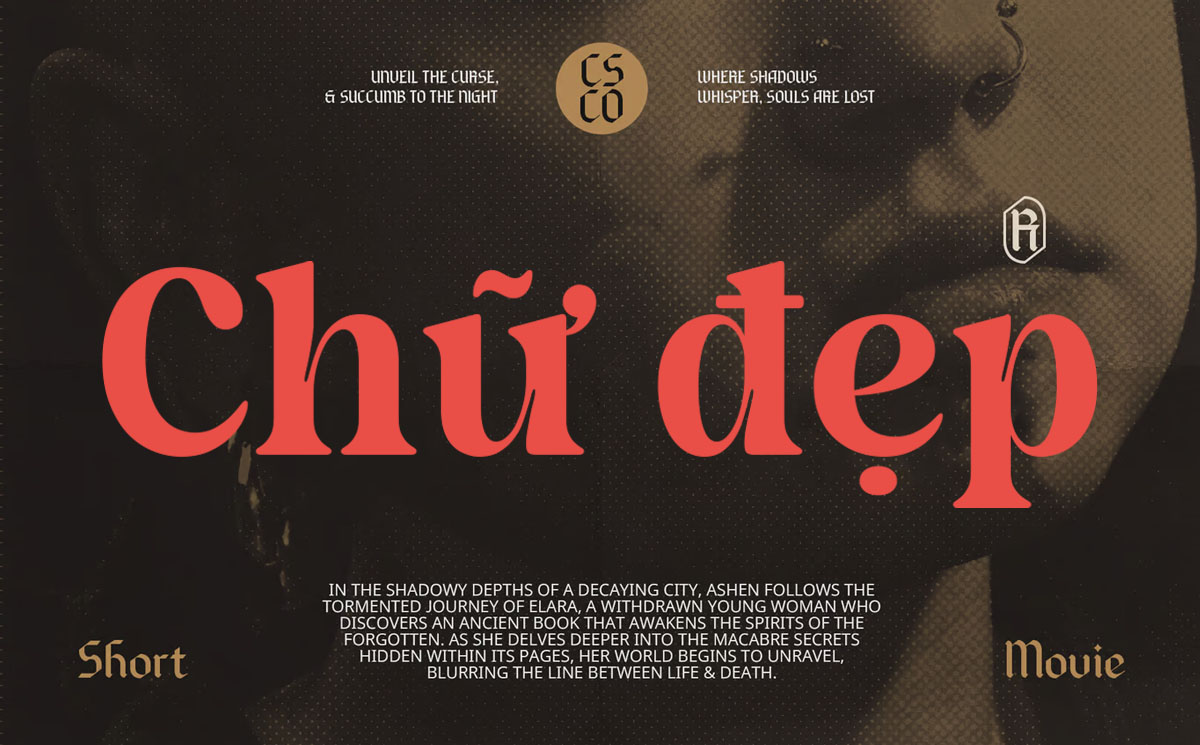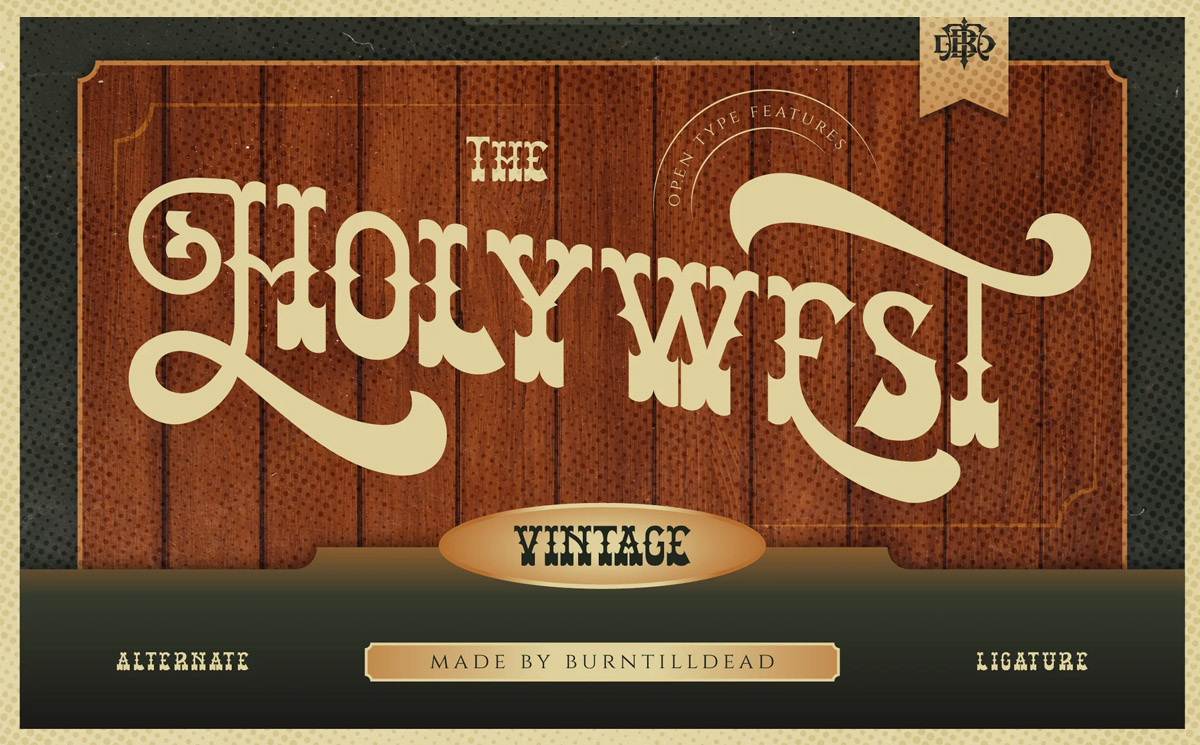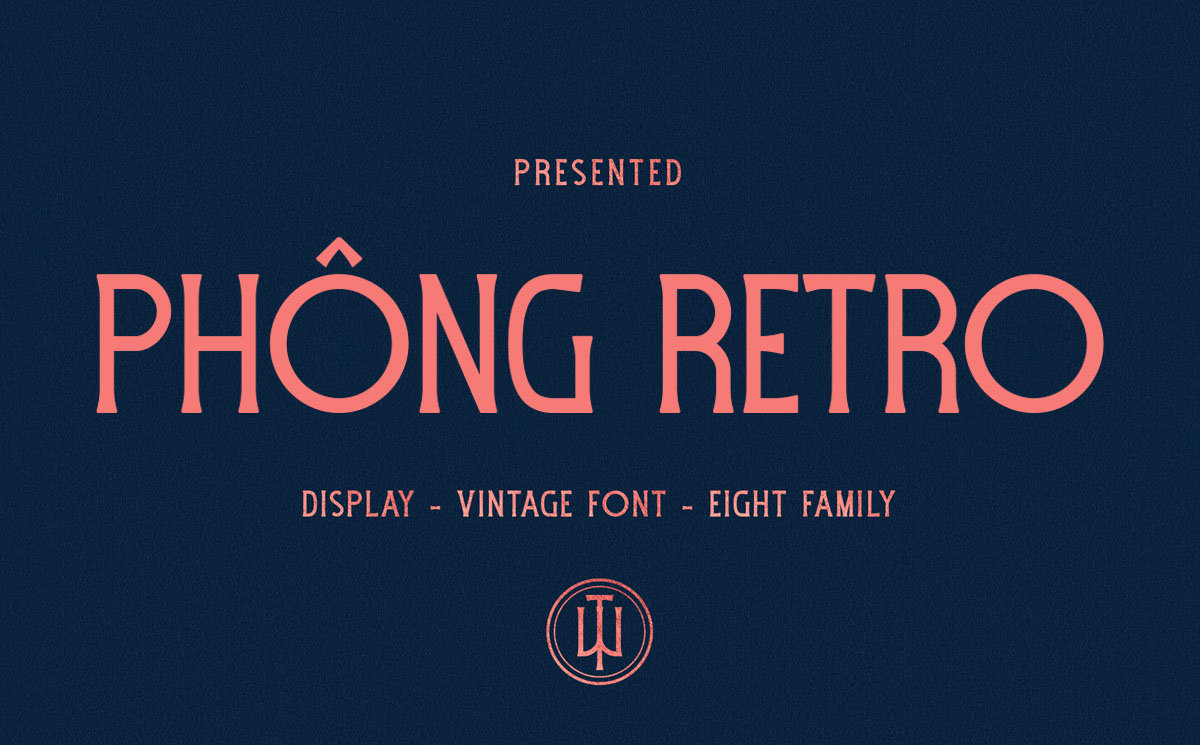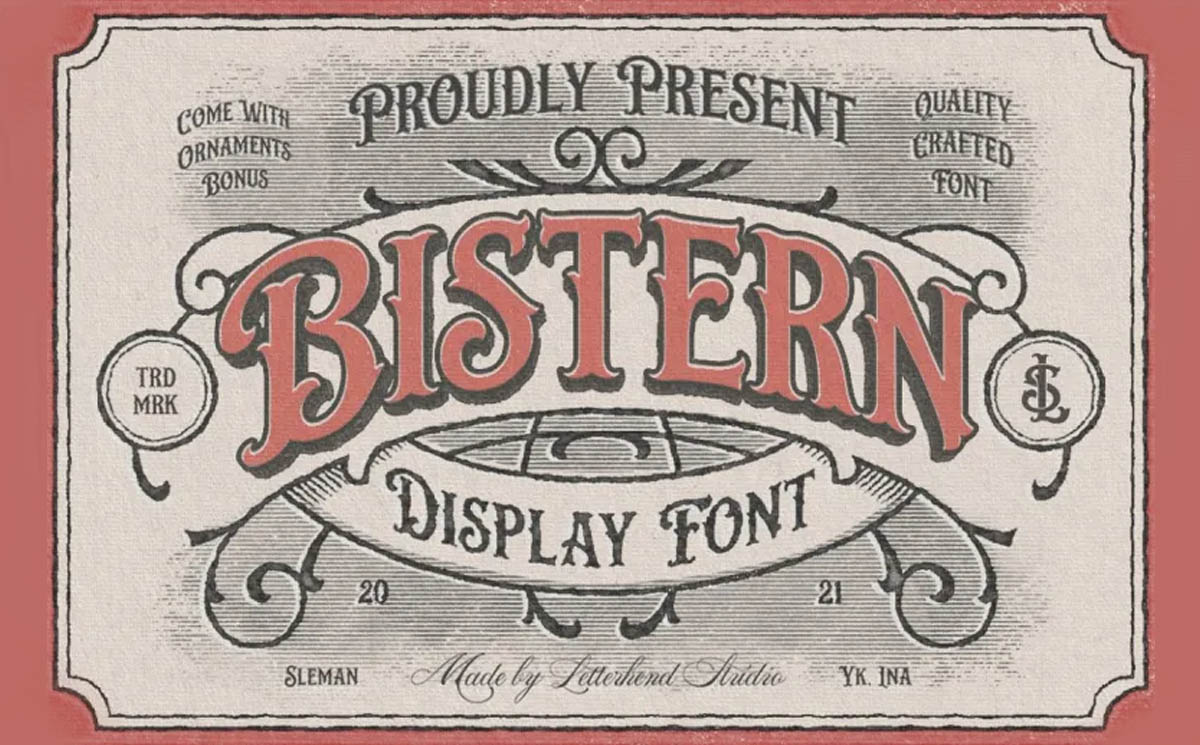
Bộ Sưu Tập 17+ Font Chữ Vintage, Font Chữ Cổ Điển Việt Hóa Đẹp Cho Thiết Kế
Bạn có cảm nhận được không? Làn sóng hoài cổ đang trỗi dậy mạnh mẽ hơn bao giờ hết trong năm 2025. Từ những MV ca nhạc triệu view, bao bì sản phẩm trendy cho đến bộ nhận diện thương hiệu của các Local Brand đình đám, phong cách Vintage/Retro đang chiếm lĩnh thị giác của chúng ta. Nó mang lại cảm giác tin cậy, ấm áp và một chút tiếc nuối đẹp đẽ về những ngày xưa cũ.
Tuy nhiên, "nỗi đau" lớn nhất của Designer Việt khi theo đuổi phong cách này chính là vấn đề font chữ vintage việt hóa. Tìm được một font đẹp trên Pinterest hay Behance thì dễ, nhưng tải về gõ tiếng Việt lại bị lỗi ô vuông, mất dấu, hoặc tệ hơn là dấu câu bay lung tung làm hỏng cả bố cục thiết kế. Chưa kể, những font chữ hệ thống mặc định thì lại quá nhàm chán và "đụng hàng" nhan nhản.
Đừng lo, fontdep.vn đã ở đây để giải quyết vấn đề đó cho bạn. Dưới đây là bộ sưu tập 17 font chữ "TH" Việt hóa độc quyền, được tuyển chọn kỹ lưỡng để đáp ứng mọi sắc thái cảm xúc: từ sự cứng cáp của thể thao thập niên 80, vẻ sang trọng quý phái của báo chí cổ điển, cho đến nét ma mị của Gothic. Hãy cùng khám phá và tải xuống ngay kho báu typography này nhé!
I. Nhóm Font Display & Retro: Tuyên ngôn cá tính cho Poster và Tiêu đề
Đây là nhóm font dành cho những ai muốn tạo ra sự bùng nổ về thị giác ngay từ cái nhìn đầu tiên. Đặc điểm chung của chúng là nét dày, thiết kế cách điệu mạnh mẽ, sinh ra để dành cho các tiêu đề (Headline), Poster quảng cáo hoặc Logo thương hiệu cần sự phá cách.
1. Font chữ TH Cungcap 13 - Font chữ thể thao cứng cáp phong cách vintage
Mở đầu danh sách là một chiến binh thực thụ mang tên TH Cungcap 13. Nhìn vào font chữ này, bạn sẽ ngay lập tức liên tưởng đến những chiếc áo khoác bóng chày (Varsity Jacket) hay các poster giải đấu thể thao sôi động của thập niên 80-90. Với cấu trúc vuông vức, các đường nét được cắt gọt dứt khoát và độ dày lớn, đây là lựa chọn số 1 để thể hiện sức mạnh và tốc độ.
- Phong cách: Thể thao (Sporty), Mạnh mẽ (Bold), Retro.
- Ứng dụng tốt nhất: Thiết kế logo đội nhóm, in ấn trên áo thun streetwear, tiêu đề banner sự kiện thể thao điện tử (Esports).
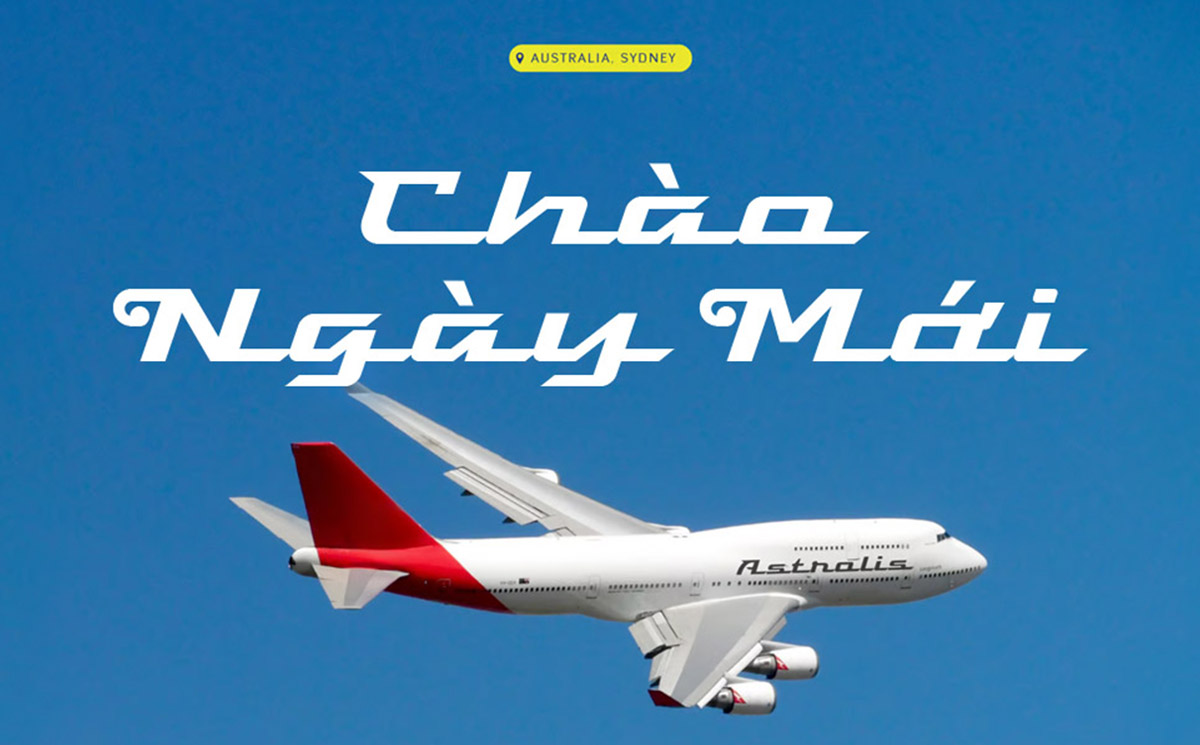
2. Phông chữ display mang phong cách retro - TH Tan Meringue Việt hóa
Nếu bạn đang tìm kiếm một sự hoài cổ nhưng vẫn mang hơi thở của Gen Z vui tươi, TH Tan Meringue chính là câu trả lời. Font chữ này sở hữu những đường cong "nhảy múa" đầy ngẫu hứng. Đặc biệt, các nét nối và bụng chữ được cách điệu phình to hoặc thu nhỏ bất quy tắc tạo nên hiệu ứng thị giác cực kỳ thú vị, giống như hương vị ngọt ngào của chiếc bánh Meringue vậy.
- Phong cách: Playful (Vui tươi), Funky, Modern Retro.
- Ứng dụng tốt nhất: Bao bì thực phẩm, menu quán cafe - bánh ngọt, thiết kế social media cho các brand mỹ phẩm teen.
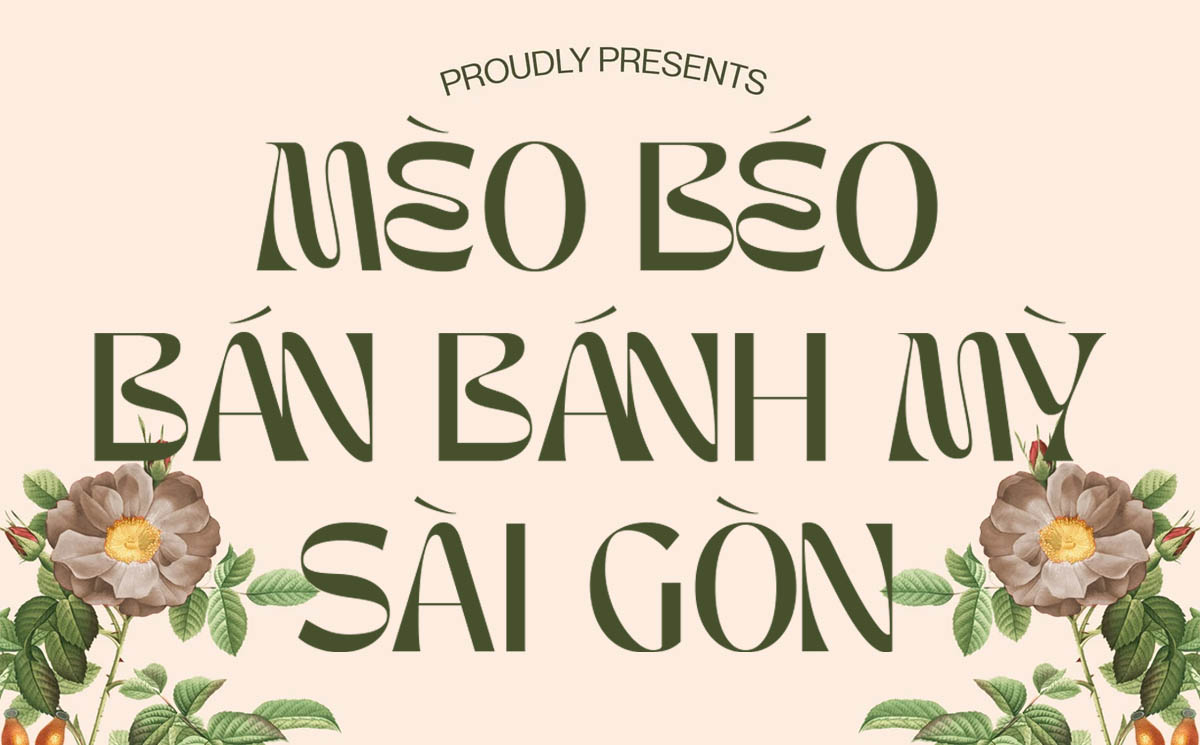
3. Font Morucas Việt hóa – Phông Chữ Display Hoài Cổ, Đậm Chất Nghệ Thuật
Lấy cảm hứng từ phong cách khắc gỗ và biển hiệu Mexico những năm đầu thế kỷ 20, TH Morucas là sự kết hợp tuyệt vời giữa cấu trúc khối vững chãi và các đường cong mềm mại ở chân chữ. Font chữ này mang lại cảm giác thủ công (craftsmanship) rất cao, khiến người xem cảm nhận được sự tỉ mỉ trong từng con chữ.
- Phong cách: Artistic (Nghệ thuật), Woodblock (Khắc gỗ), Vintage.
- Ứng dụng tốt nhất: Biển hiệu cửa hàng (Signage), bìa tạp chí nghệ thuật, nhãn mác rượu hoặc coffee.
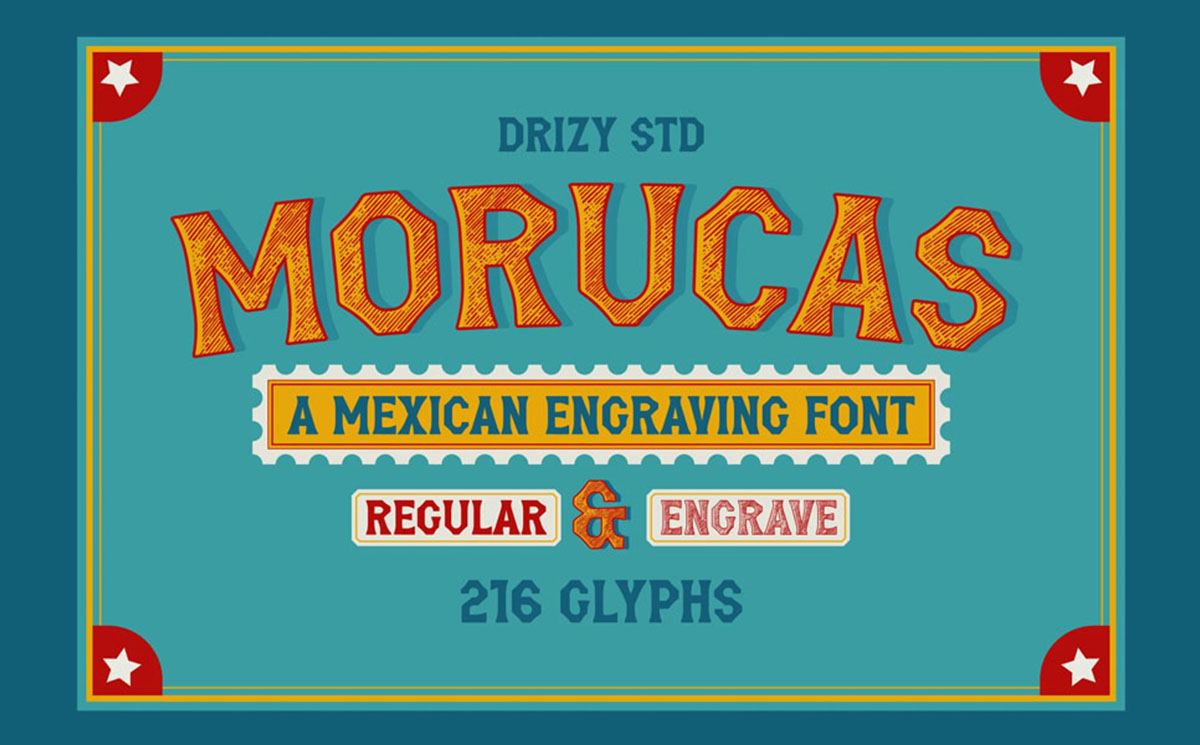
4. Phông chữ viết tay phong cách retro cổ điển - TH Relgone Việt hóa
Khác với sự nắn nót của máy móc, TH Relgone mô phỏng lại nét bút lông hoặc phấn bảng với độ đậm nhạt tự nhiên. Font chữ này mang lại cảm giác mộc mạc, gần gũi và "rất đời". Nó giống như dòng chữ được viết vội trên bảng menu của một quán ăn ven đường thập niên 90, đầy sự mời gọi và thân thiện.
- Phong cách: Vẽ tay, vẽ bằng bút lông, tranh vẽ biển hiệu cổ điển.
- Ứng dụng tốt nhất: Quotes (trích dẫn) trên mạng xã hội, thiết kế bao bì sản phẩm organic/thủ công, poster nhạc Indie.
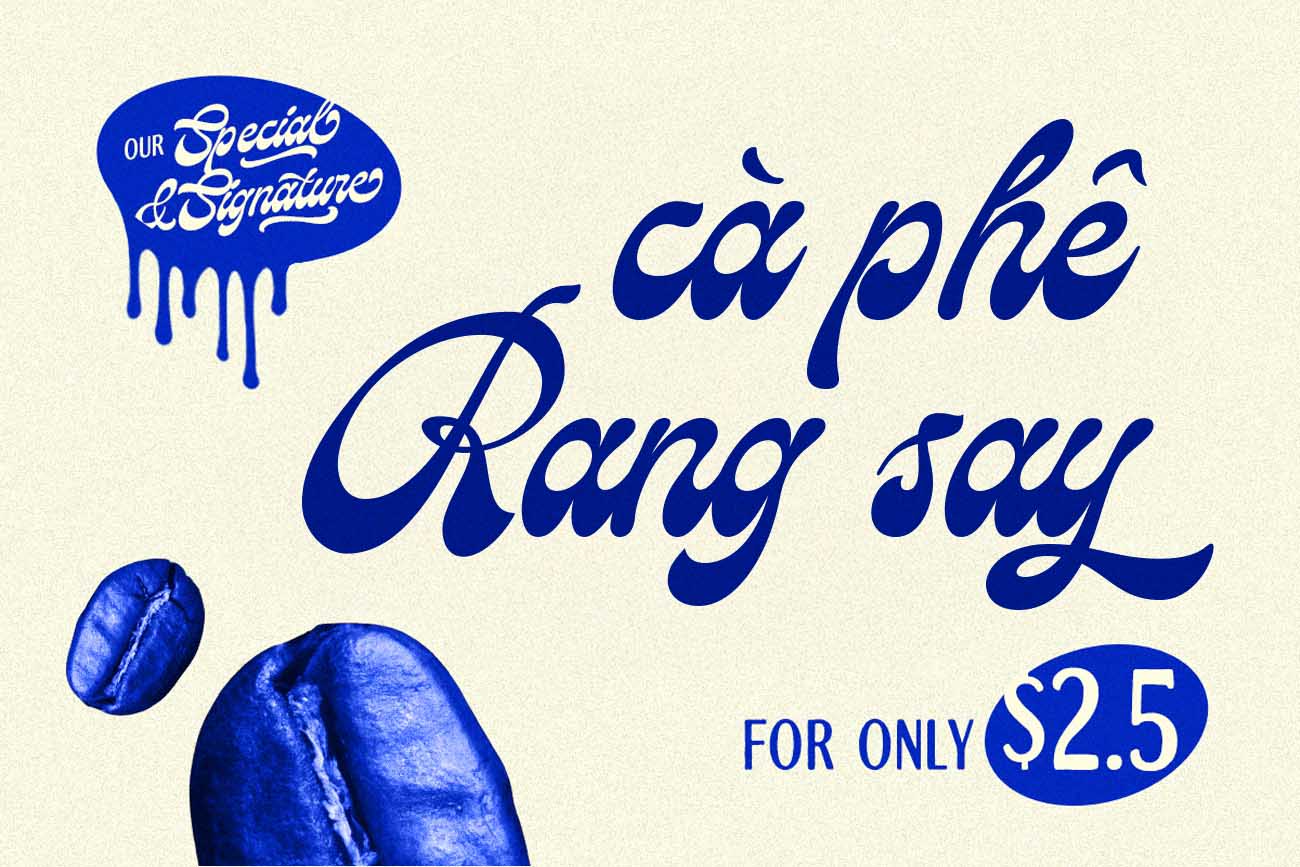
II. Nhóm Font Serif Cổ Điển & Sang Trọng: Vẻ đẹp thanh lịch vượt thời gian
Nếu dự án của bạn cần sự tin cậy, uy tín và một chút xa xỉ (luxury), hãy chọn Font Serif (chữ có chân). Nhóm font này tại fontdep.vn được Việt hóa cực kỳ chỉn chu, giữ nguyên được cái "hồn" quý phái của bản gốc.
1. Font chữ Việt hóa cổ điển mang phong cách Vintage | TH Vintage 1
Đúng như tên gọi, TH Vintage 1 là hiện thân của những tờ báo giấy cũ kỹ hay những tấm tem phiếu thời bao cấp. Font chữ có chân rõ ràng, độ tương phản vừa phải giúp văn bản dễ đọc ngay cả ở kích thước nhỏ. Đây là font chữ khơi gợi ký ức mạnh mẽ nhất trong bộ sưu tập.
- Phong cách: Newspaper (Báo chí), Nostalgic (Hoài niệm).
- Ứng dụng tốt nhất: Dàn trang sách, tiêu đề bài viết blog lịch sử, poster phim tài liệu, thiệp mời phong cách 19xx.
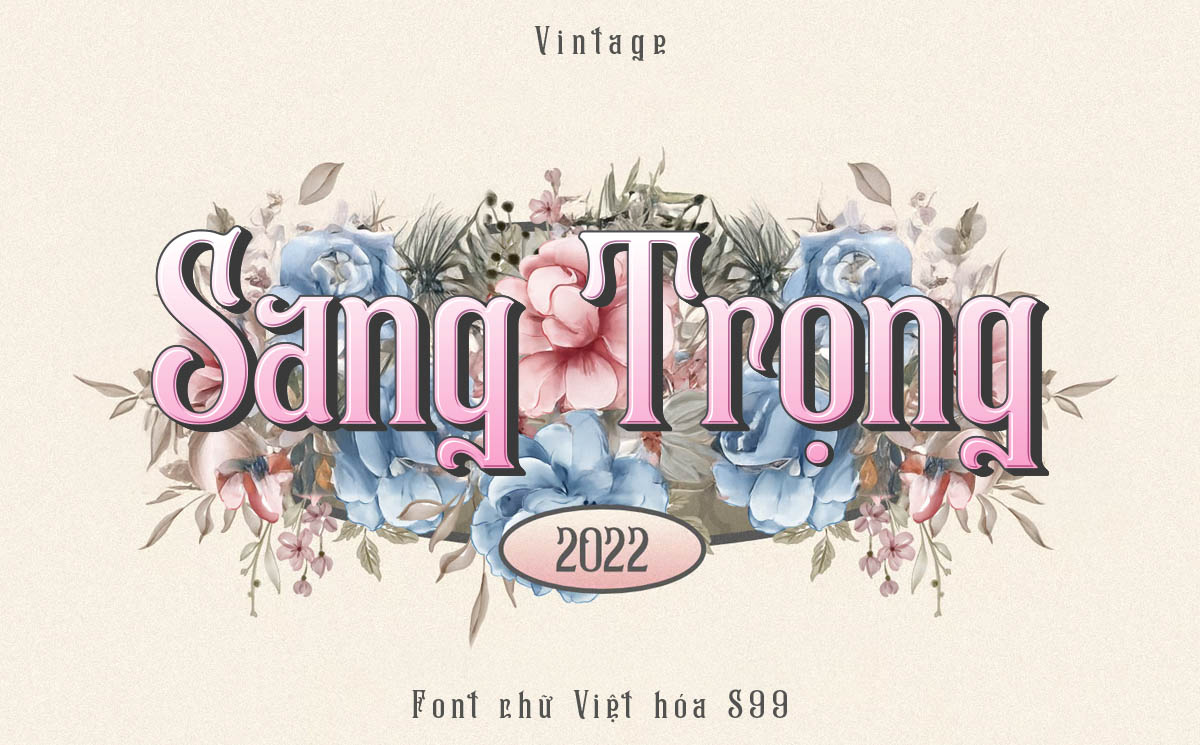
2. Font chữ phong cách cổ điển và sang trọng TH Castio Việt hóa
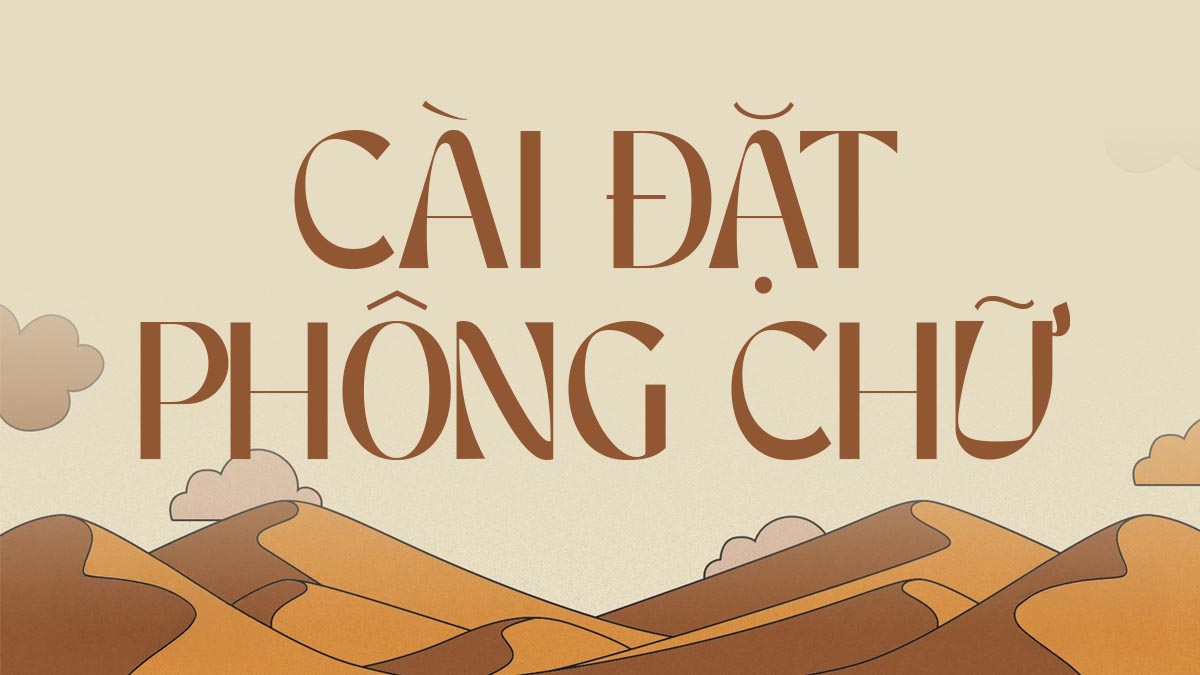
VI. Lời Kết